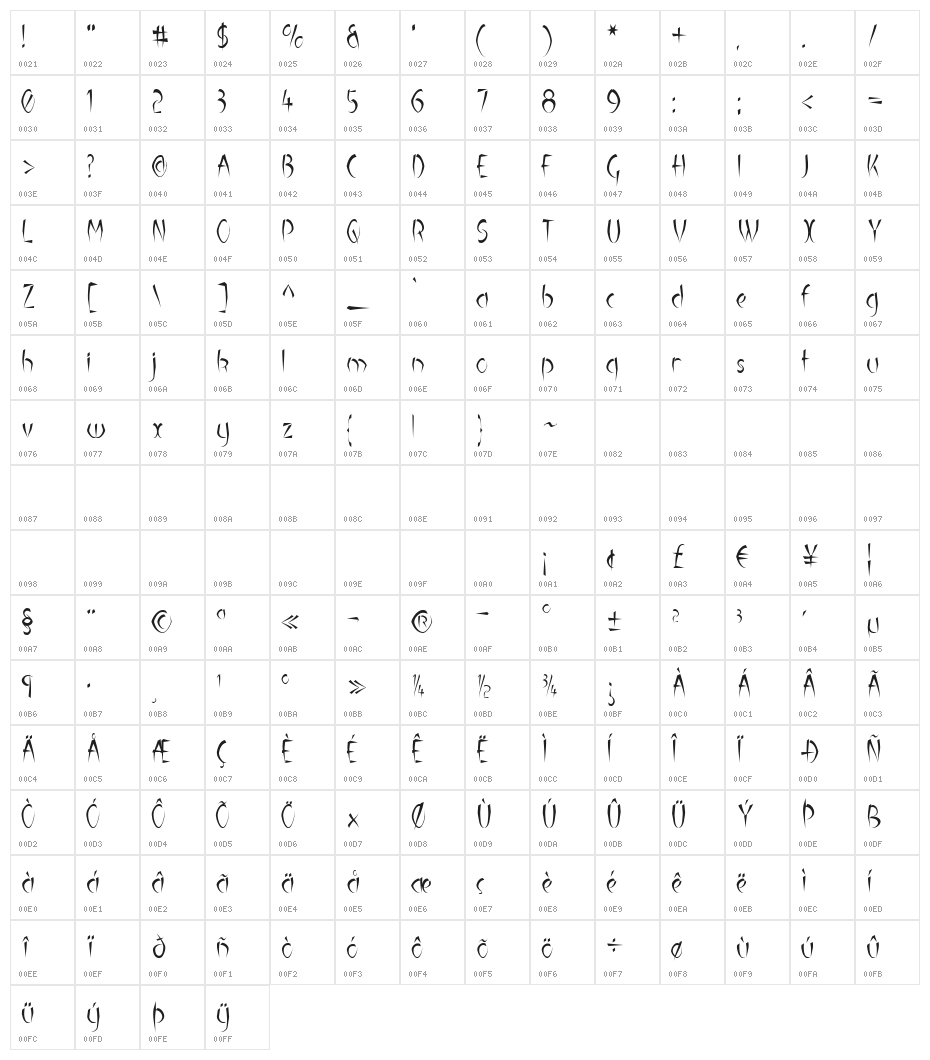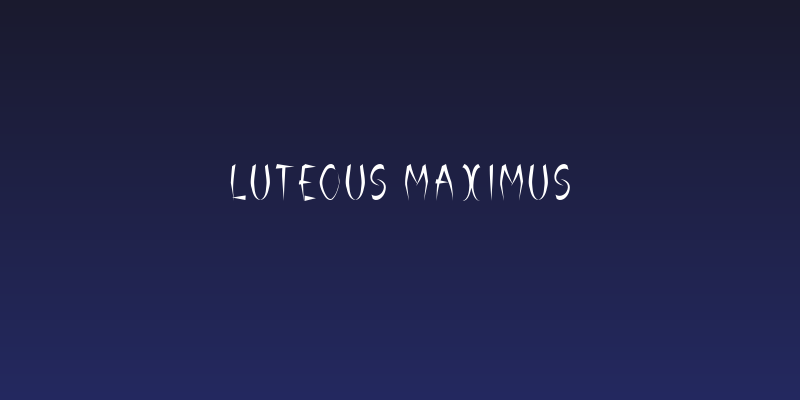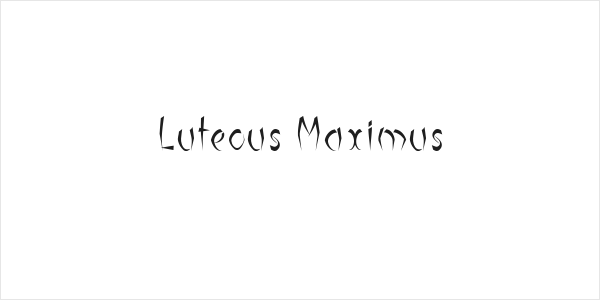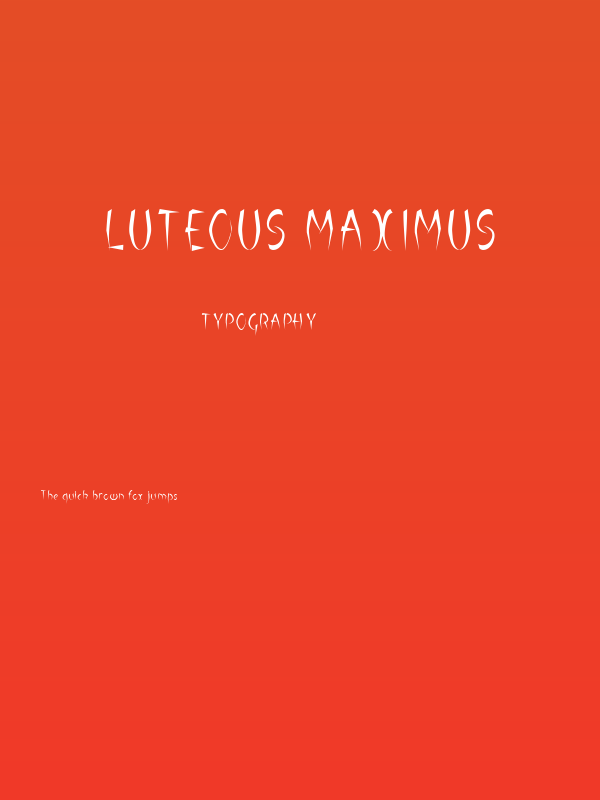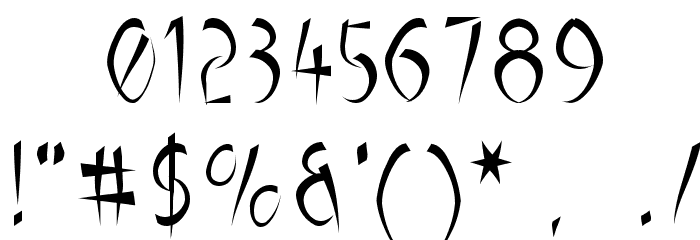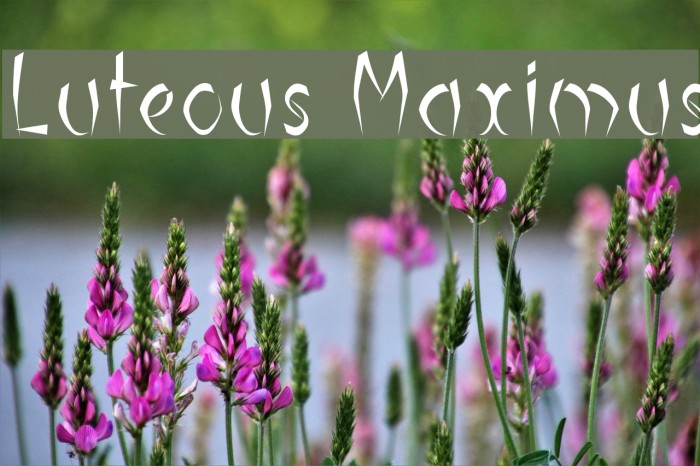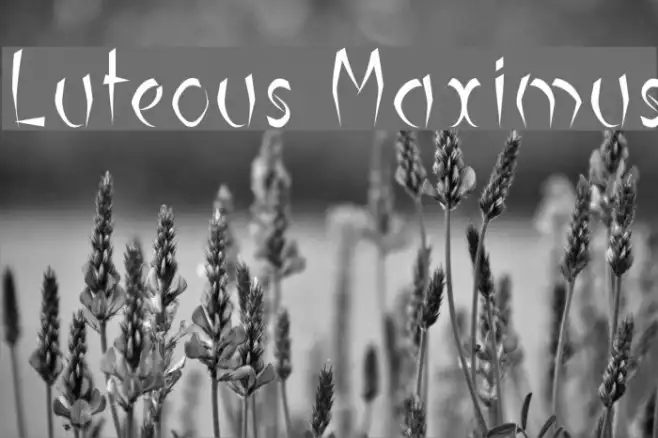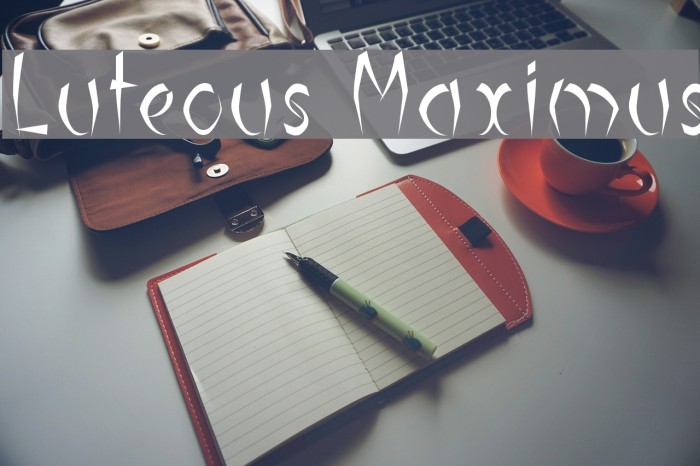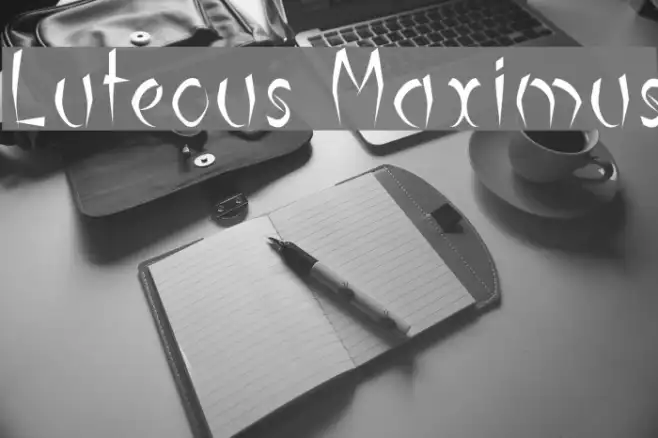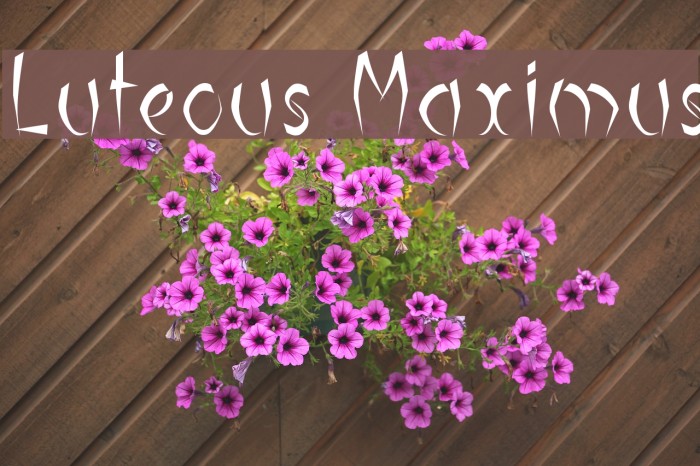
Luteous Maximus Font
| Gesamtstil | Modern, Edgy |
| Vorgeschlagene Projekte | Ideal for music album covers, video game titles, posters, and branding that requires a bold, edgy look. |